Cách chọn font cho landing page khóa học online để tăng độ tin cậy
Một font quá trang trí có thể làm landing page kém nghiêm túc. Một font quá mảnh có thể đẹp trên desktop nhưng khó đọc trên điện thoại.
Landing page khóa học online không chỉ cần đẹp. Trang phải khiến người học tin rằng khóa học đáng tiền, giảng viên đủ chuyên môn và nội dung đủ rõ để họ đăng ký. Trong đó, font chữ ảnh hưởng rất mạnh đến cảm giác tin cậy, khả năng đọc và tỷ lệ bấm CTA.
Một font quá trang trí có thể làm landing page kém nghiêm túc. Một font quá mảnh có thể đẹp trên desktop nhưng khó đọc trên điện thoại. Một font không hỗ trợ tiếng Việt tốt sẽ làm các từ như "khóa học", "học viên", "đăng ký", "chứng chỉ" bị lệch dấu hoặc thiếu chuyên nghiệp.
Bài viết này hướng dẫn cách chọn font cho landing page khóa học online, từ hero, headline, nội dung dài, CTA, testimonial đến phần curriculum. Cuối bài có gợi ý font TH Việt hóa phù hợp cho nhiều dạng khóa học khác nhau.
Vì sao font ảnh hưởng đến độ tin cậy của landing page khóa học?
Người mua khóa học thường phải ra quyết định dựa trên thông tin: ai dạy, học được gì, lộ trình ra sao, có phù hợp không và đăng ký thế nào. Nếu font khó đọc, thiếu nhất quán hoặc quá "trang trí", người xem sẽ cảm thấy trang thiếu chuyên nghiệp.
Font tốt giúp thông tin được phân cấp rõ. Headline phải nổi bật, mô tả phải dễ đọc, CTA phải rõ hành động, testimonial phải đáng tin và nội dung chương trình học phải đủ mạch lạc. Tất cả những phần này đều cần font đúng vai trò.
Với landing page tiếng Việt, độ tin cậy còn nằm ở dấu tiếng Việt. Dấu bị lệch hoặc quá nhỏ khiến trang trông giống bản thiết kế chưa hoàn thiện. Vì vậy hãy ưu tiên font Việt hóa hoặc font đã kiểm tra tốt với tiếng Việt.
Chọn font cho từng phần trên landing page
Ở hero section, bạn có thể dùng font display hoặc sans-serif mạnh để làm headline. Nhưng headline cần ngắn, rõ và đọc được trên mobile. Nếu dùng font cá tính, hãy giữ phần mô tả bên dưới bằng font dễ đọc hơn.
Ở phần nội dung khóa học, curriculum, FAQ và mô tả lợi ích, font cần ổn định. Sans-serif gọn hoặc serif dễ đọc sẽ tốt hơn script/display. Đây là khu vực người xem đọc lâu, nên độ rõ quan trọng hơn sự nổi bật.
Ở CTA, font nên rõ, dày vừa đủ và tạo cảm giác hành động. Các cụm như "Đăng ký ngay", "Nhận tư vấn", "Tải lộ trình học" cần dễ đọc ngay lập tức. Đừng dùng font quá mềm hoặc quá mảnh cho nút CTA.
Gợi ý font TH Việt hóa cho landing page khóa học online
Các font dưới đây được chọn theo từng nhóm ứng dụng trên landing page: font đọc nội dung, font headline, font công nghệ, font thân thiện và font tạo cảm xúc. Bạn có thể phối 2-3 font trong cùng một trang, nhưng nên giữ hệ thống nhất quán.
1. TH Algance
TH Algance là sans serif tối giản, dễ đọc, hợp phần body, mô tả khóa học, FAQ, testimonial và các đoạn nội dung cần tạo cảm giác rõ ràng. Khi dùng trên landing page, hãy test thử headline, CTA và một đoạn mô tả khóa học để đảm bảo font rõ trên cả desktop lẫn mobile.
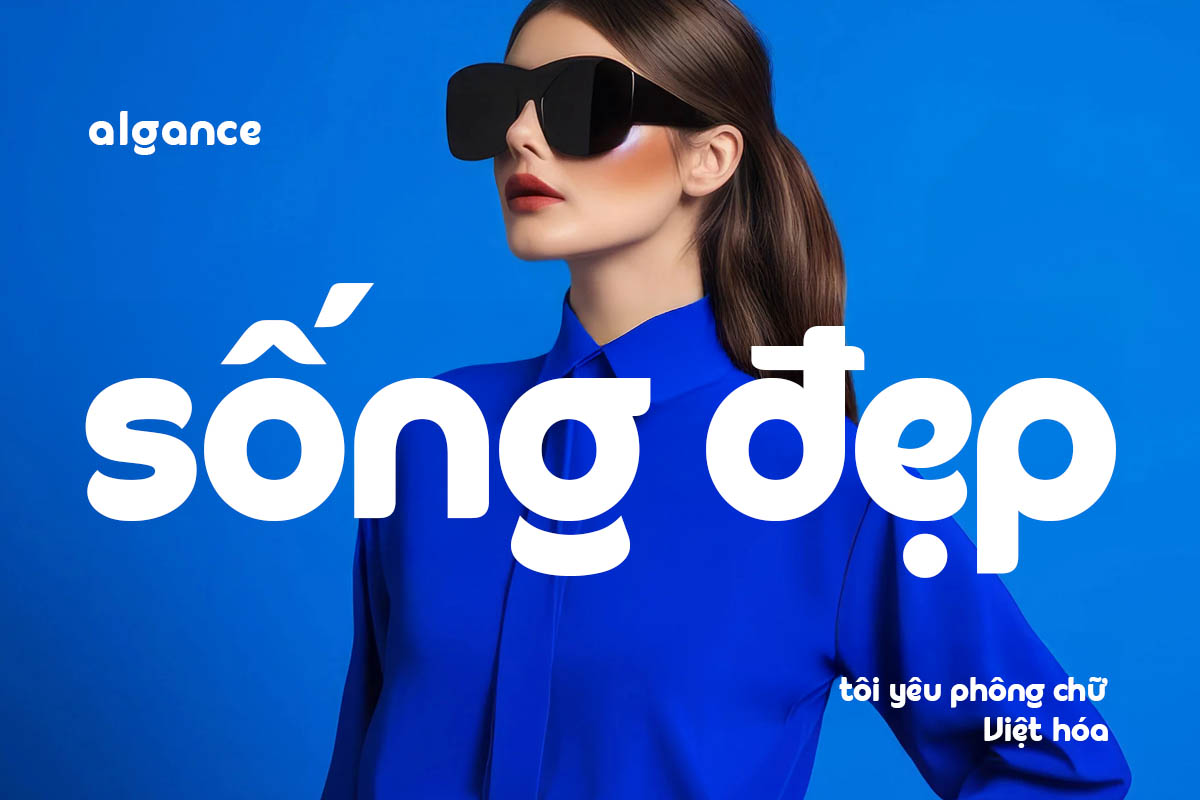
2. TH Giabe
TH Giabe là sans serif display hiện đại, phù hợp headline hero, tiêu đề section, banner tuyển sinh và các landing page khóa học trẻ trung. Khi dùng trên landing page, hãy test thử headline, CTA và một đoạn mô tả khóa học để đảm bảo font rõ trên cả desktop lẫn mobile.
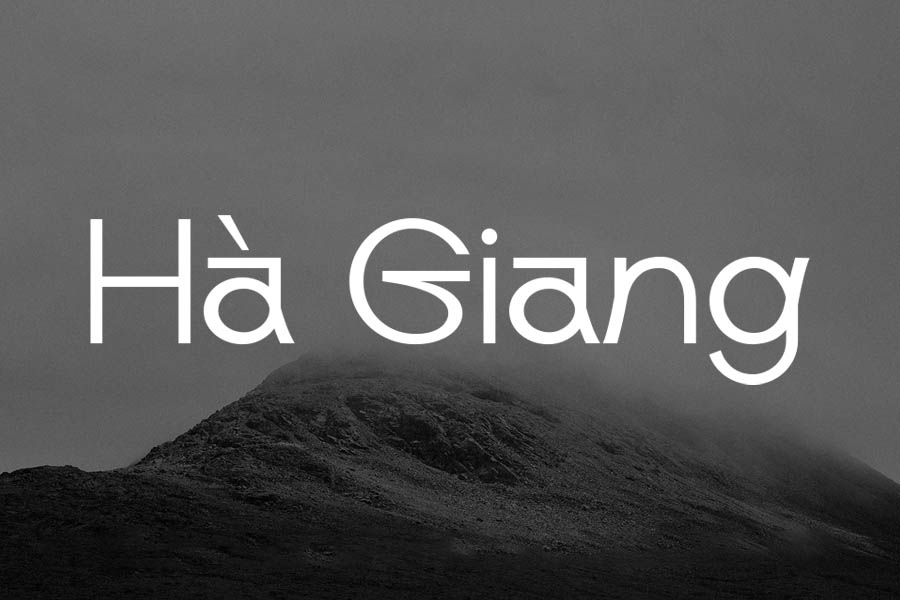
3. TH Belly & Park
TH Belly & Park là font condensed giúp headline ngắn gọn và tiết kiệm không gian, hợp hero, CTA, countdown, ưu đãi và section khóa học bán mạnh. Khi dùng trên landing page, hãy test thử headline, CTA và một đoạn mô tả khóa học để đảm bảo font rõ trên cả desktop lẫn mobile.
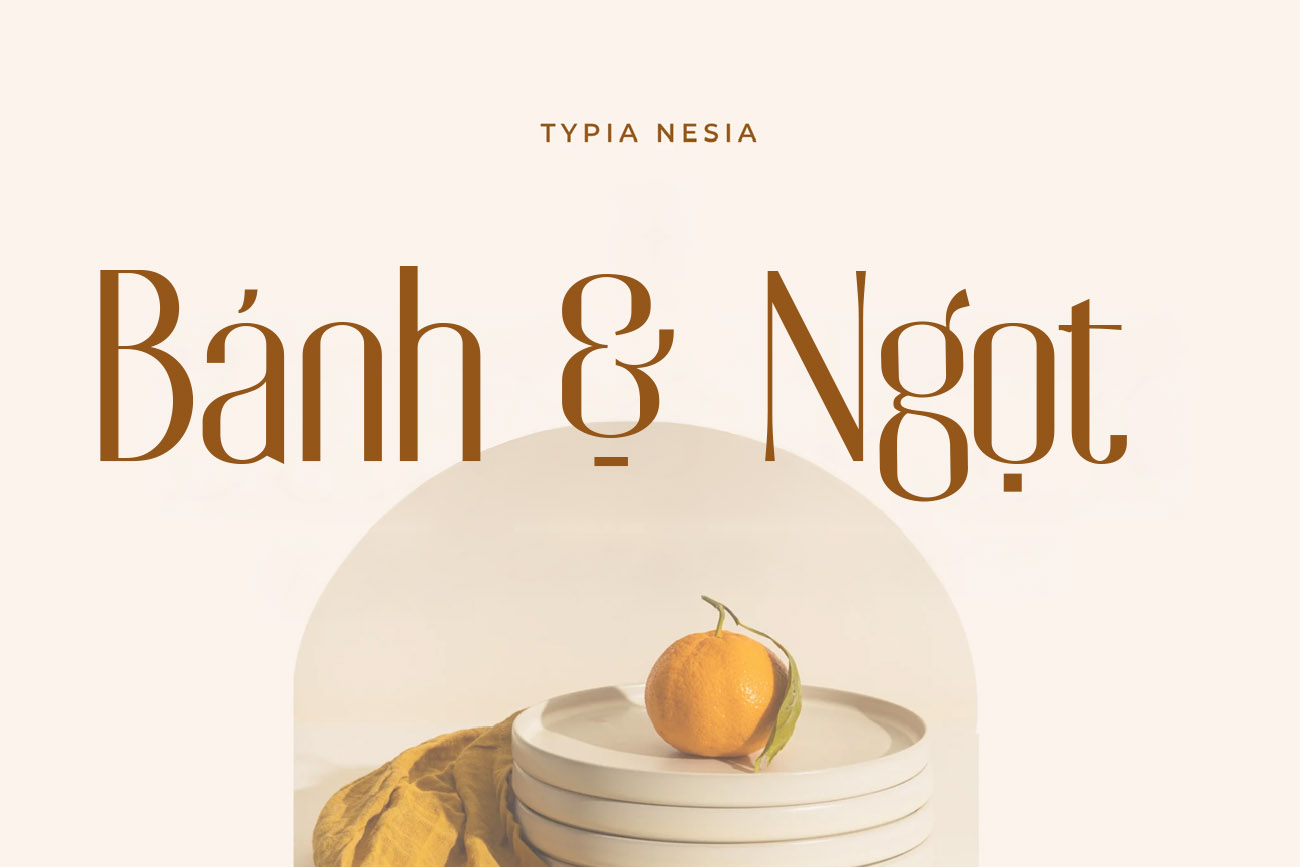
4. TH Revans Serif
TH Revans Serif là serif cổ điển hiện đại, hợp khóa học chuyên môn, coaching, tài chính, ngoại ngữ, kỹ năng quản trị và landing page cần độ tin cậy cao. Khi dùng trên landing page, hãy test thử headline, CTA và một đoạn mô tả khóa học để đảm bảo font rõ trên cả desktop lẫn mobile.
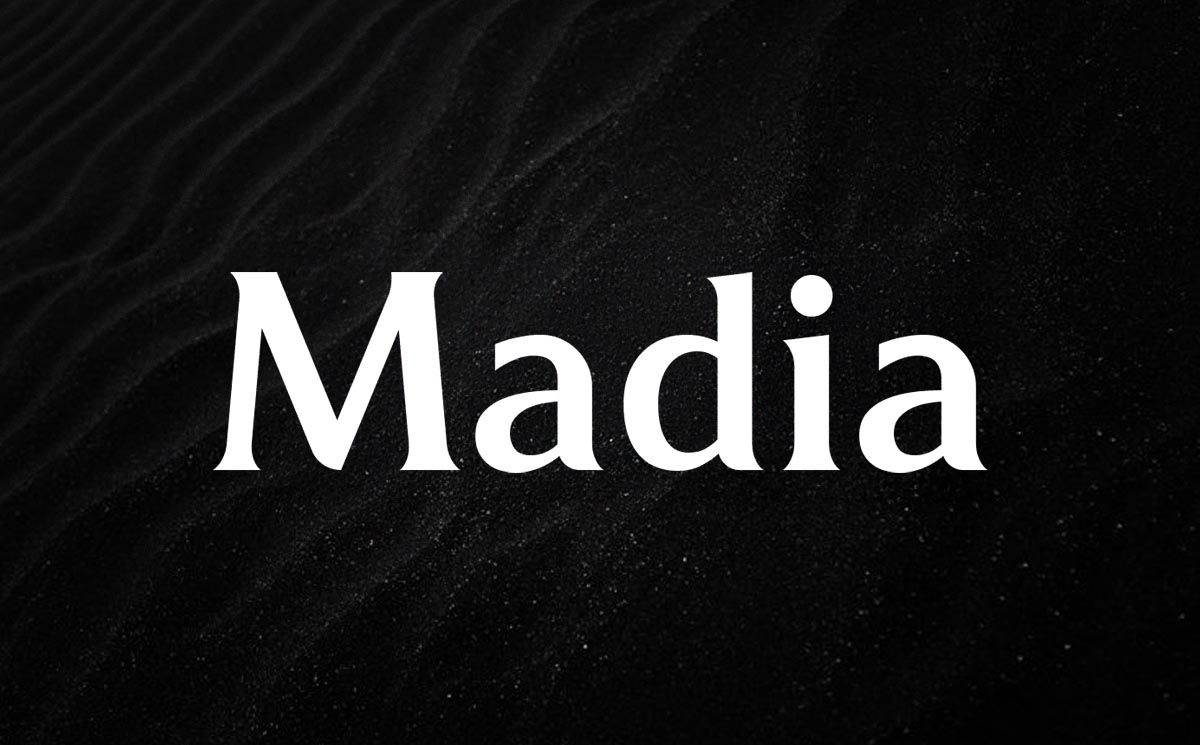
5. TH Selvia Genatu
TH Selvia Genatu là serif sang trọng, hợp khóa học nghệ thuật, lifestyle, beauty, branding cá nhân và landing page cần cảm giác cao cấp. Khi dùng trên landing page, hãy test thử headline, CTA và một đoạn mô tả khóa học để đảm bảo font rõ trên cả desktop lẫn mobile.
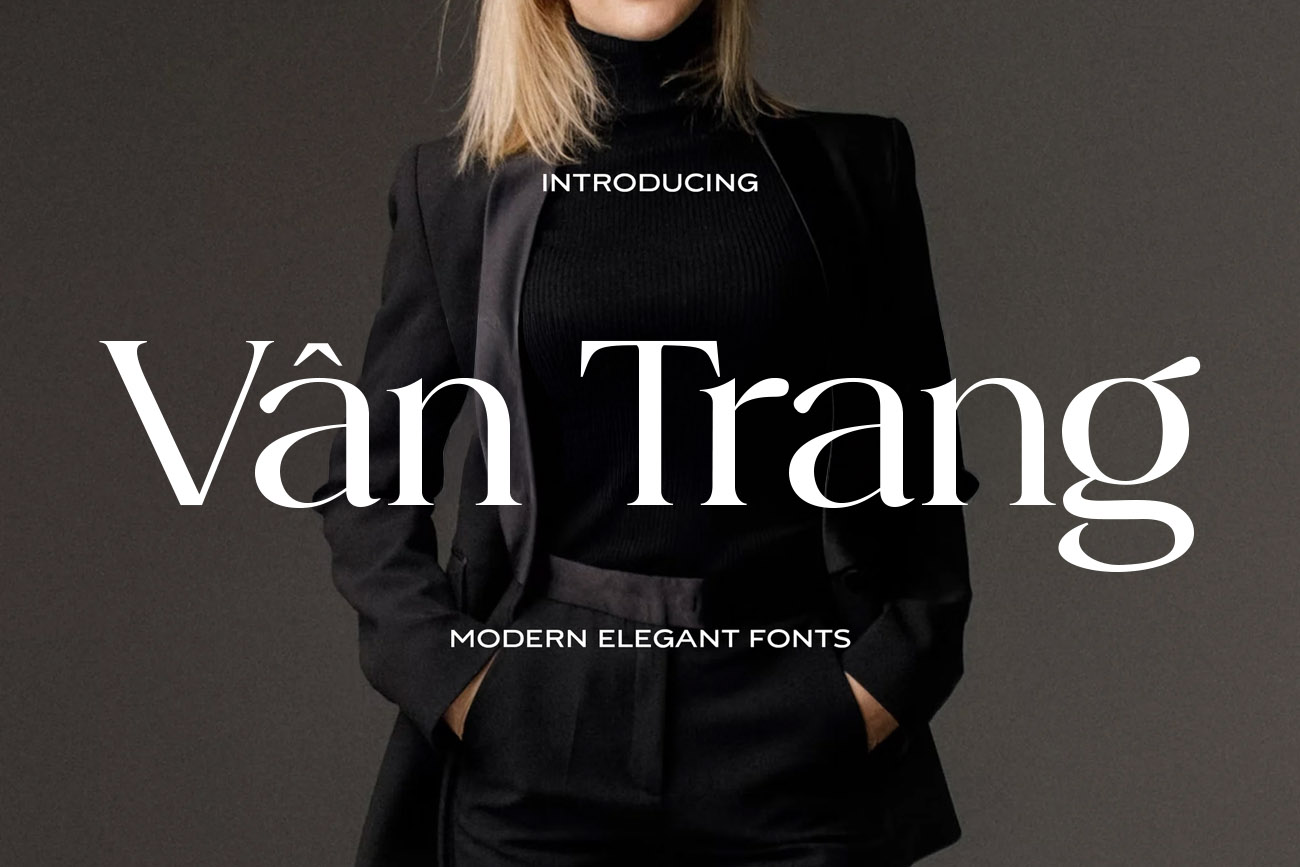
6. TH Axiome
TH Axiome là font công nghệ tối giản, phù hợp landing page khóa học AI, lập trình, UI/UX, automation, sản phẩm số và e-learning hiện đại. Khi dùng trên landing page, hãy test thử headline, CTA và một đoạn mô tả khóa học để đảm bảo font rõ trên cả desktop lẫn mobile.
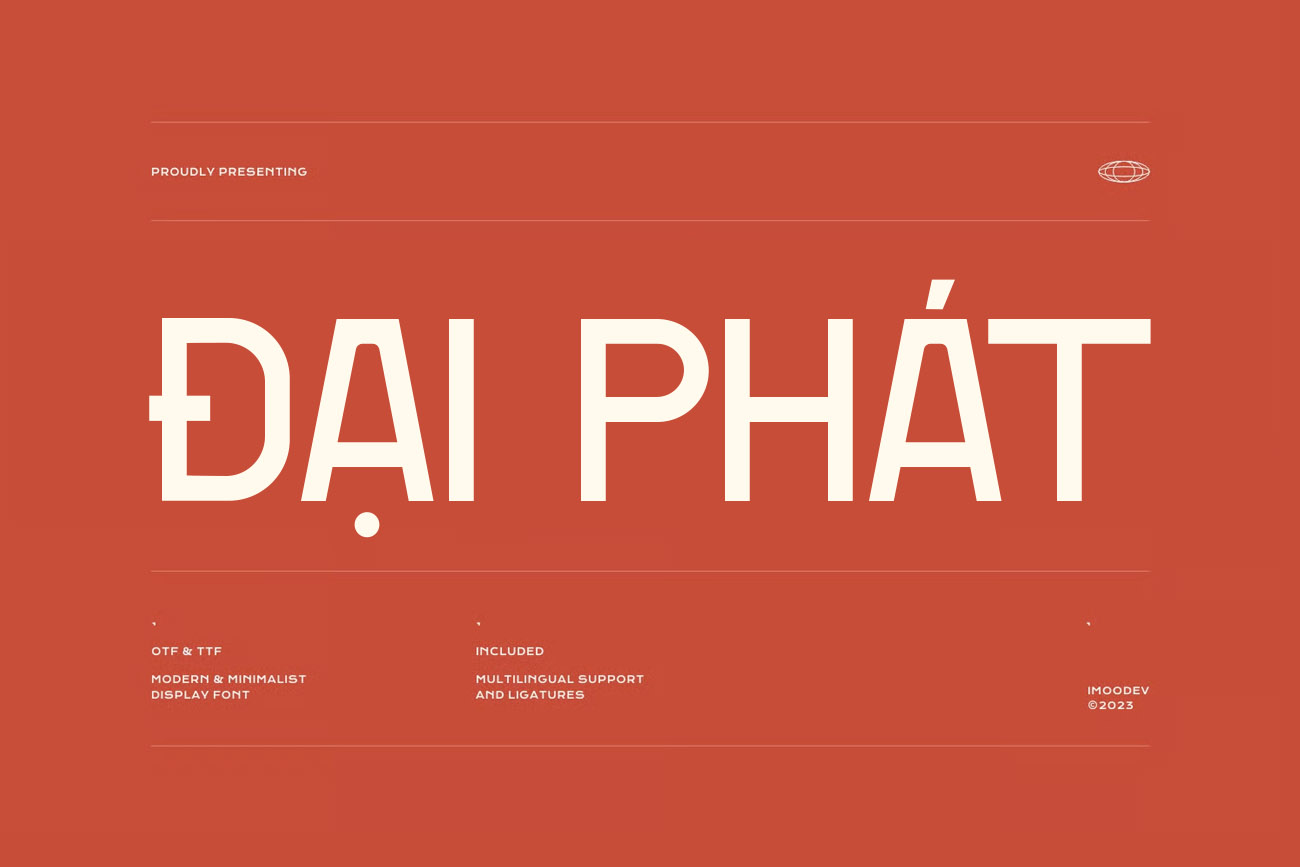
7. TH Seona Display
TH Seona Display là font công nghệ nổi bật, hợp hero khóa học công nghệ, webinar, bootcamp, workshop kỹ thuật và các CTA cần tạo cảm giác mới. Khi dùng trên landing page, hãy test thử headline, CTA và một đoạn mô tả khóa học để đảm bảo font rõ trên cả desktop lẫn mobile.
Font landing page khóa học online cần tạo độ tin cậy, dễ đọc và hỗ trợ chuyển đổi. Hãy chọn font theo vai trò: headline nổi bật, nội dung rõ ràng, CTA dễ bấm, testimonial thân thiện và curriculum mạch lạc.
Các font TH Việt hóa trong bài là điểm khởi đầu tốt để thiết kế landing page khóa học, e-learning, webinar và chương trình tuyển sinh. Hãy test font trên nội dung thật trước khi chốt để landing page vừa đẹp vừa đáng tin.